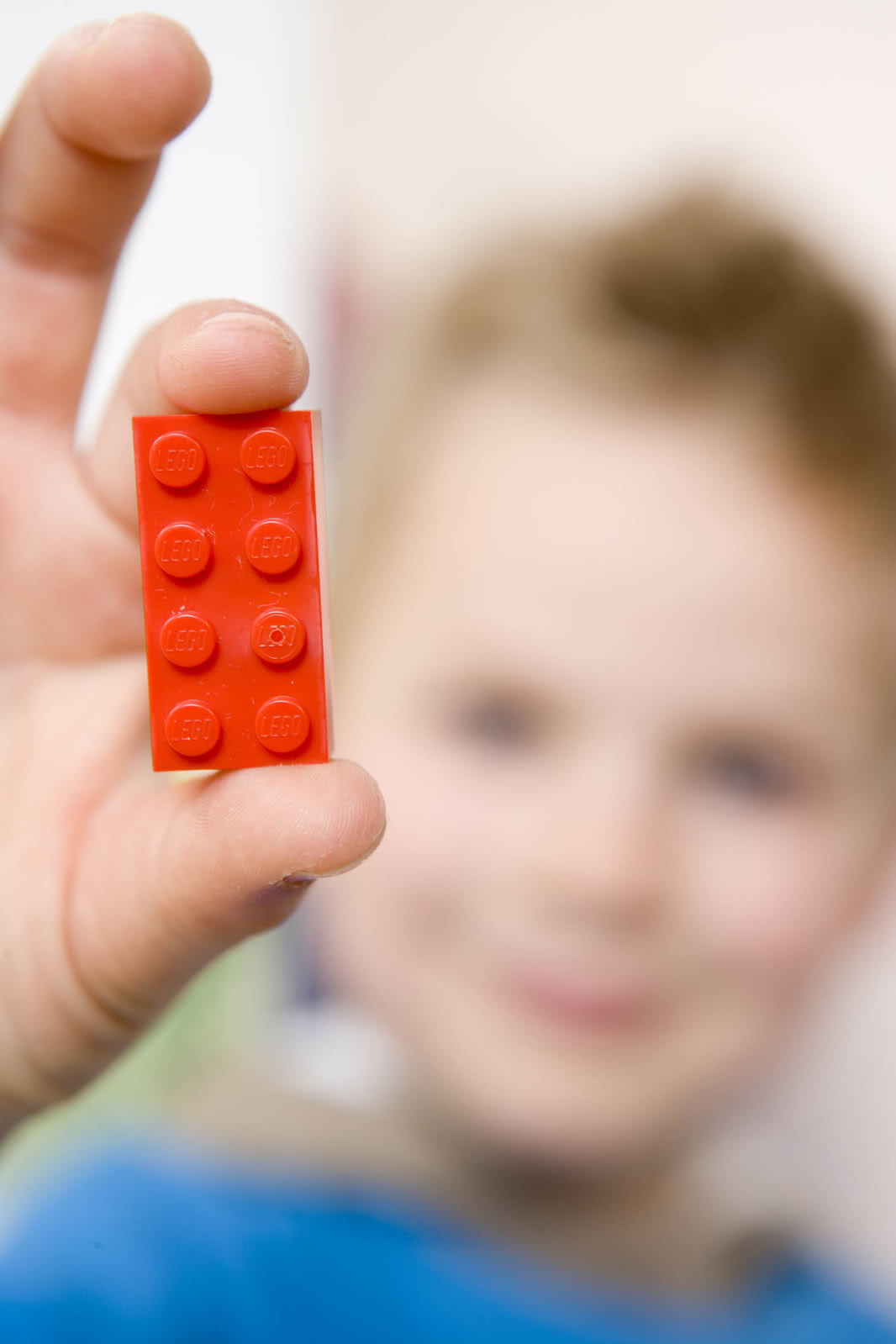
Welche Typo ist auf den Legonoppen zusehen?
Bei so einem Weltunternehmen kann ich mir nicht vorstellen, dass die einen dahergelaufenenen »Stock«-Font nehmen. Ganz abgesehen davon, dass ich auf dem (zugegeben Riesenbild) nichts Vernünftiges erkennen kann.
also auf meinem Lego-Technik-Karton von vor 10 Jahren ist das so eine DIN/ISO-Schablonenschrift (welche genau, und ob die einen Namen hat, kann ich nicht sagen).
Die ist breiter als die gezeigte, aber sehr ähnlich.
Jeder der einen Legostein hat kann ja mal daraufschauen, vielleicht kann jemand eine ähnliche Typo entdecken...